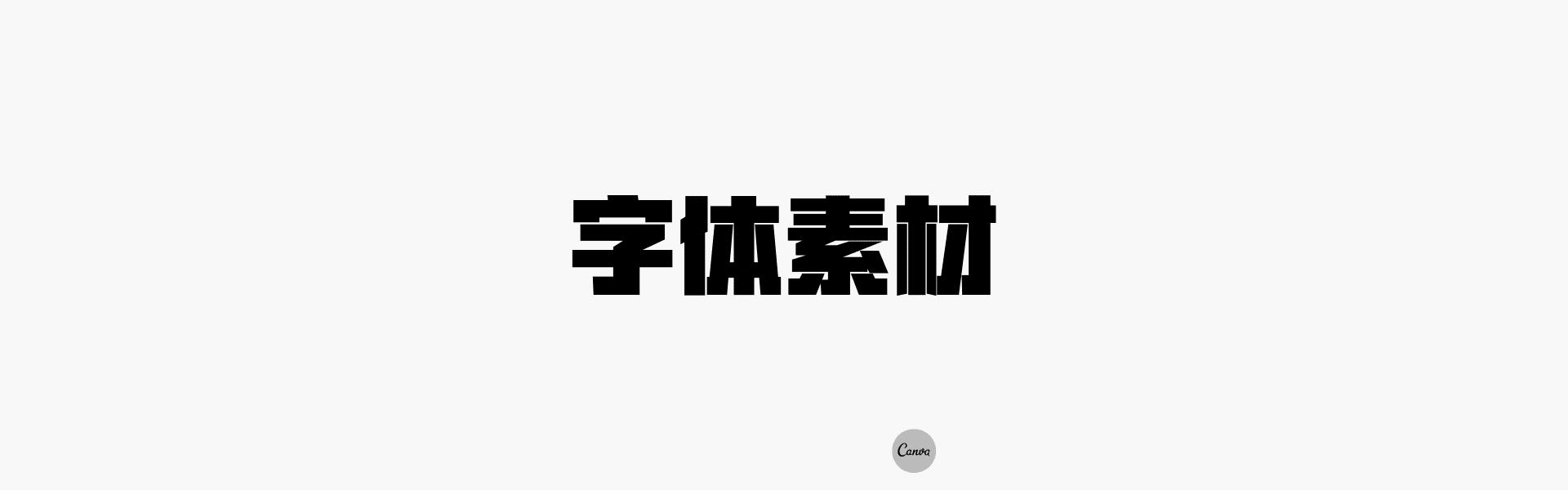
现代社会的字体设计数不胜数,每个设计师都有自己所青睐的几款字体,在一撇一捺之间传递着文字的魅力。字体素材(在新标签页或窗口中打开)对于设计师来书是一项重要的资源,近年来频繁发生的字体侵权事件数量直线上升,人们的版权意识也越来越深入,字体素材的使用范围也变得窄小,特别是对于商用来说,字体的选择对于设计师来说也变得艰难。
Adobe和Google联合发布的思源字体,让东亚地区的设计师们有了新的选择。思源字体,是专为东亚地区打造的“字体榜样”,可以不受限制的使用于商业。在字体界中,稍有个不留神,就容易侵权的这个时代,以微软雅黑事件最受著名。我们每天在word中使用的微软雅黑,一旦被用于商业,没有购买使用版权就会造成侵权,这是方正集团的设计作品,每年都有设计师们不小心就有了侵权行为。
非衬线体思源黑体和衬线体思源宋体的发布,给了设计师们更多的选择。在电子屏幕的显示上和印刷打印上,思源字体比很多字体的可读性更强,能够优化人们的感官视觉。思源宋体和黑体在视觉上的重心是往下沉的,但思源宋体的设计更偏于现代化。思源字体的存在最大的特点就是免费并且兼容性更高,这也是思源广泛传播使用的主要因素。
站酷成立于2006年,至今有七款免费字体可供使用。
站酷文艺体,这是一款2018年发布的可供免费使用的字体(包括商用),从名字我们就可以感知到这款字体所传递的气息,文艺风十足,以简洁有力的笔画表达别致的清新淡雅。
站酷酷黑体,于2016年发布使用,在站酷十周年之际发布了站酷酷黑体验版,在字体的体形上更为宽而粗,在视觉的呈现上更为醒目。
站酷小薇LOGO体,是设计师送给女儿的生日礼物,所以这款字体被打上“因爱而生”的标签。笔画间留出了足够的间隙,无论放大或缩小都能够给人良好的视觉体验。
站酷快乐体、站酷庆科黄油体、站酷高端黑体以及供西文使用的站酷意大利体,都是站酷旗下供社会免费使用的字体。